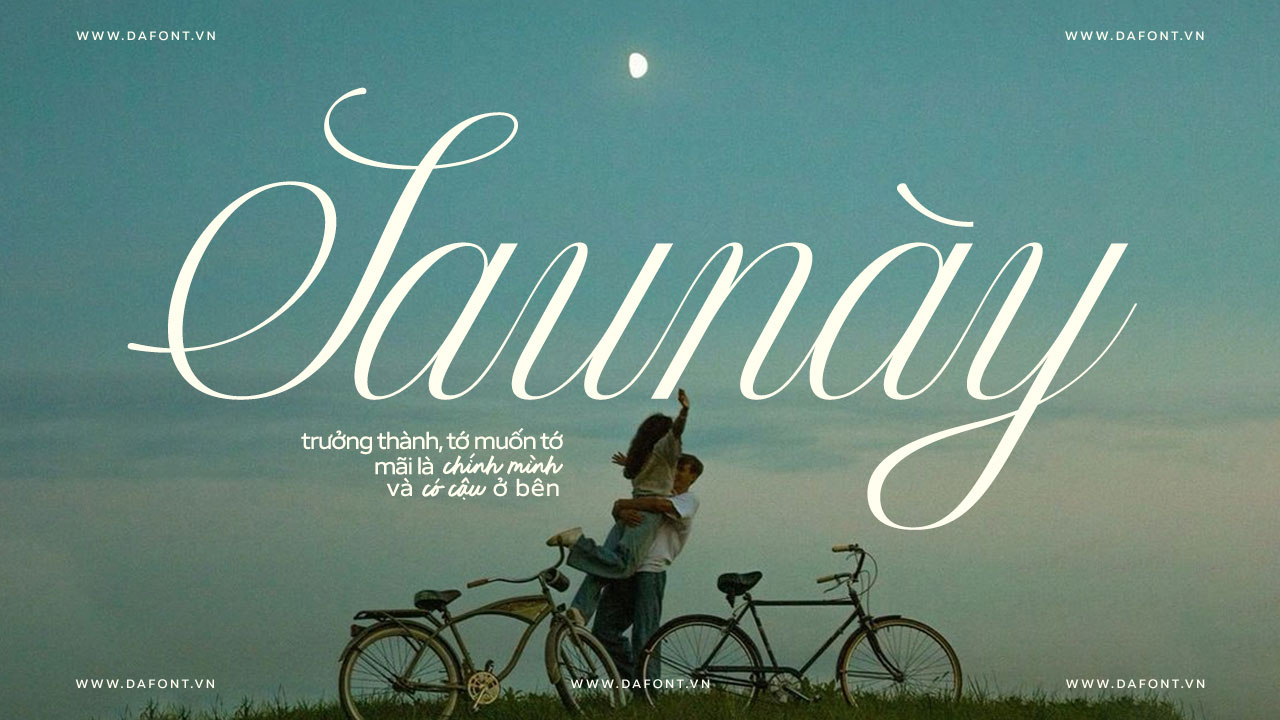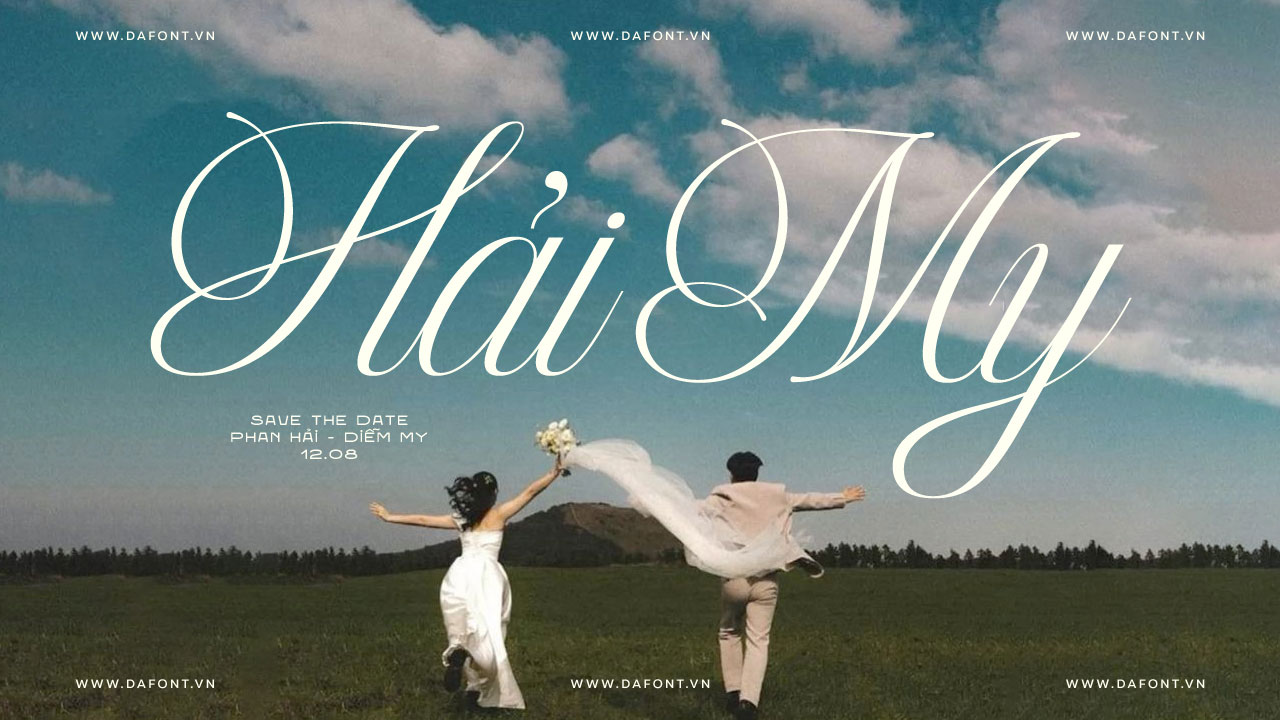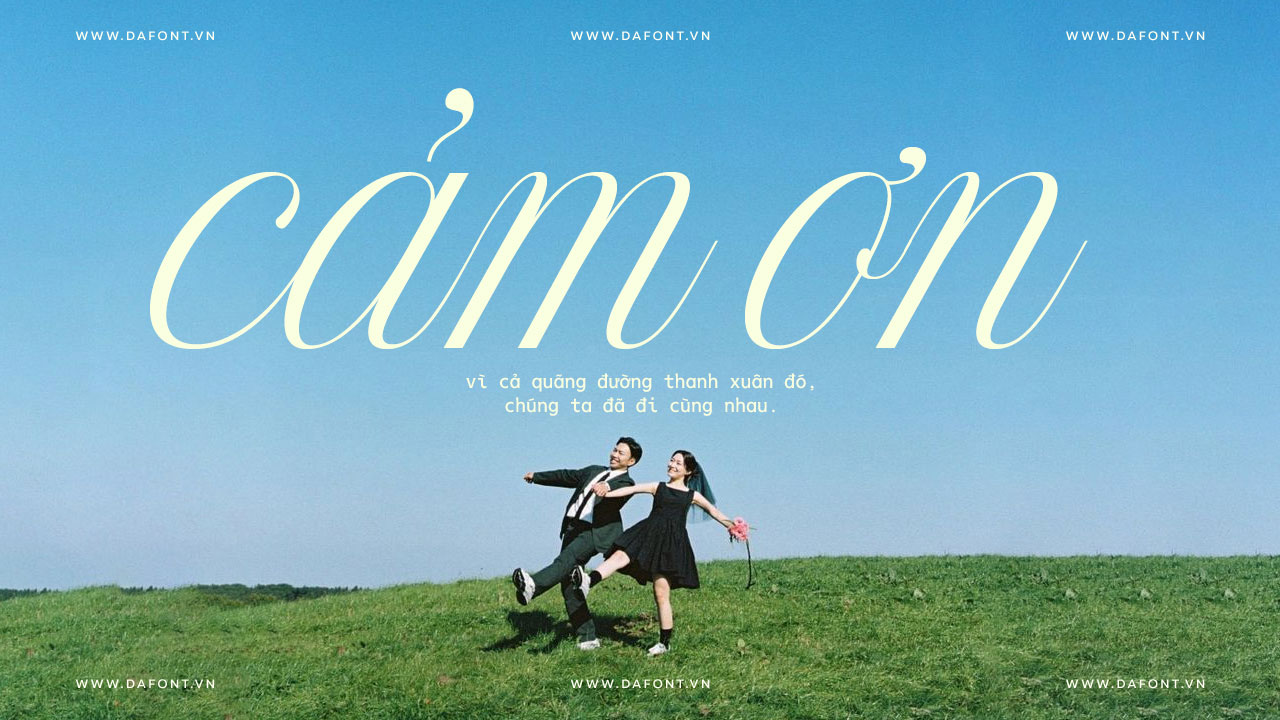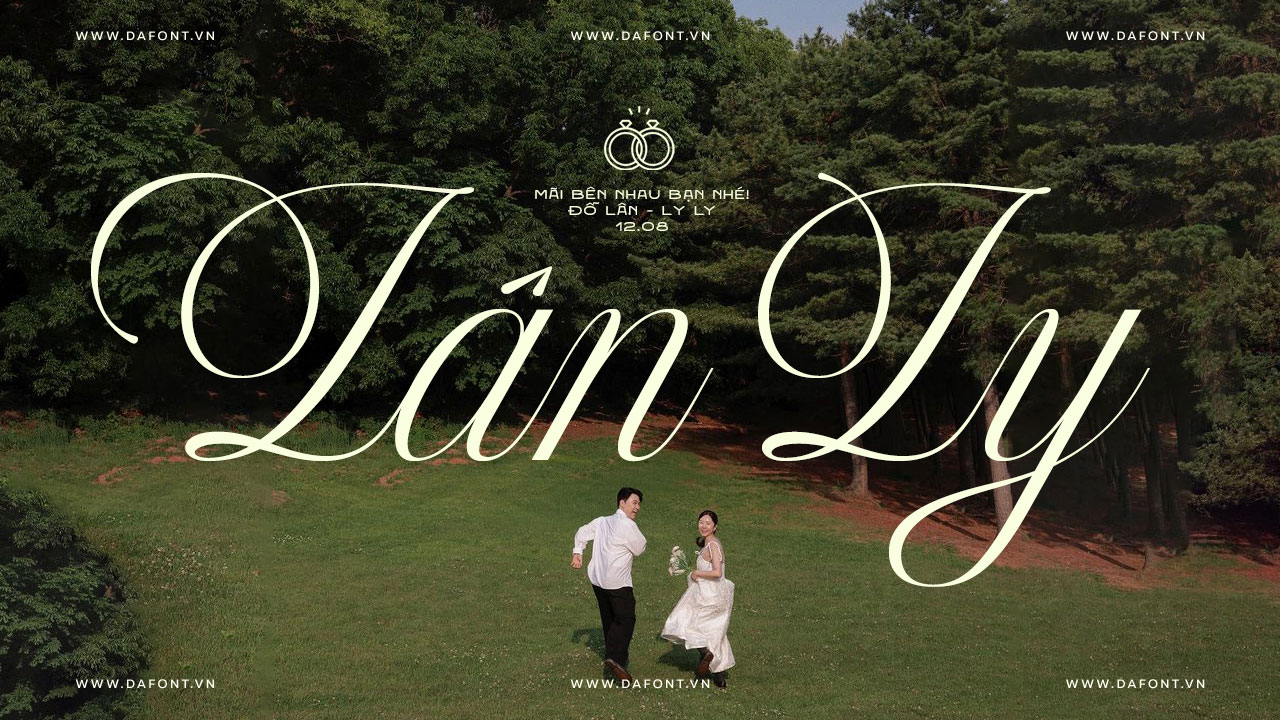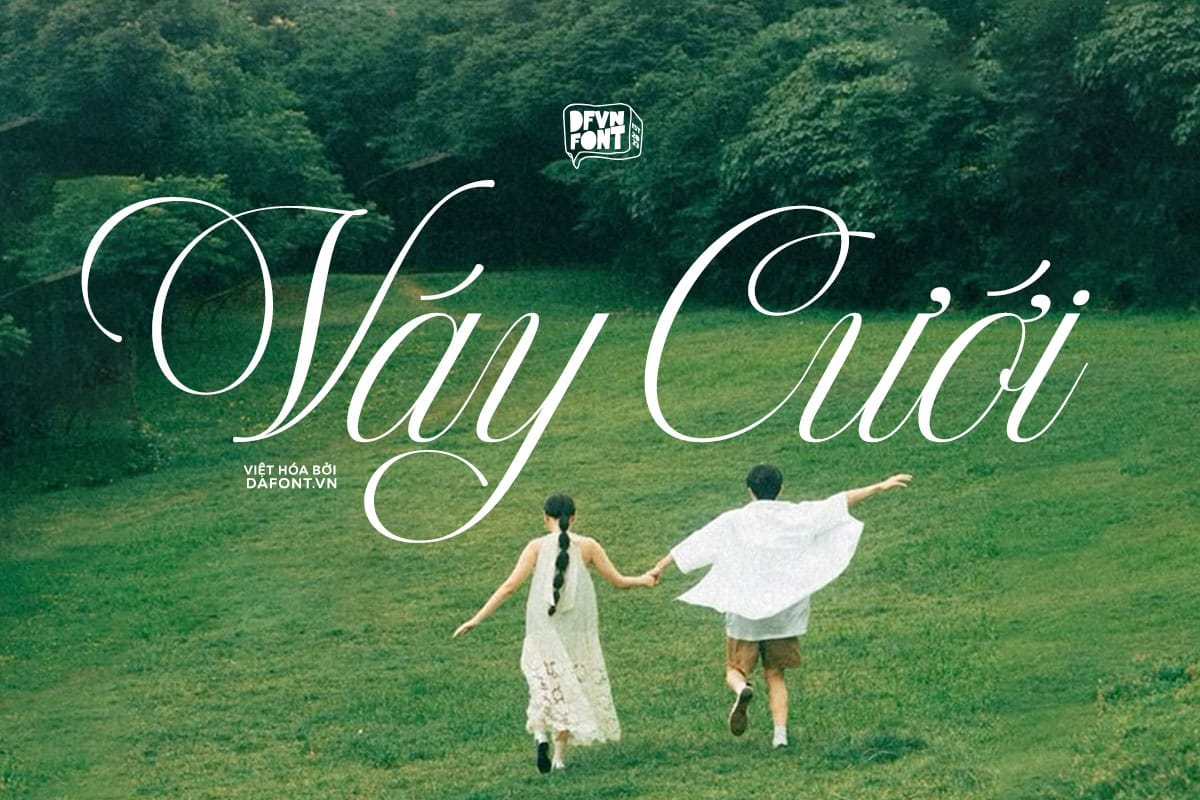
DFVN Kaelyna Script – Font viết tay thời thượng cho thiết kế sang trọng
Kaelyna Script là một font chữ viết tay hiện đại mang phong cách calligraphy đặc trưng bởi sự bay bổng, tinh tế và sang trọng, Kaelyna Script là lựa chọn lý tưởng cho những dự án thiết kế cao cấp như logo, thiệp cưới, trích dẫn hay đồ hoạ hoặc thương hiệu.
Đặc điểm nổi bật DFVN Kaelyna Script
DFVN Kaelyna Script là một font chữ nổi bật với phong cách thư pháp hiện đại, mang đến vẻ đẹp sang trọng và tinh tế nhờ các nét chữ viết tay mềm mại, uốn lượn đẹp mắt. Đây là lựa chọn lý tưởng cho các dự án thiết kế cao cấp.
Với tính thẩm mỹ cao, Kaelyna Script rất phù hợp cho các ứng dụng thực tế như branding, thiết kế thiệp cưới, hoặc bao bì sản phẩm, giúp nâng tầm giá trị thương hiệu và sản phẩm.
Font được DFVN thiết kế lại toàn bộ dấu, mang đến vẻ đẹp tinh tế và sang trọng hơn hẳn so với bản gốc. Bên cạnh đó, toàn bộ ký tự và dấu đều được tối ưu hóa kỹ lưỡng, kết hợp với kerning chuẩn xác giúp nâng cao trải nghiệm thị giác.
Phù hợp cho nhiều dự án thiết kế
DFVN Kaelyna Script là lựa chọn lý tưởng cho nhiều loại dự án:
- Branding và Logo: Tạo logo chuyên nghiệp và nhận diện thương hiệu độc đáo.
- Thiệp cưới và Thiệp mời: Mang lại cảm giác lãng mạn và tinh tế cho các sự kiện đặc biệt.
- Nhãn mác và Bao bì sản phẩm: Nâng cao giá trị thẩm mỹ cho sản phẩm cao cấp.
- Bài đăng mạng xã hội: Thu hút sự chú ý với typography đẹp mắt trên Instagram, Facebook, Tiktok, v.v.
- Quảng cáo và Thiết kế sản phẩm: Sử dụng trong các chiến dịch quảng cáo hoặc thiết kế sản phẩm để tạo điểm nhấn.
DFVN Kaelyna Script Preview